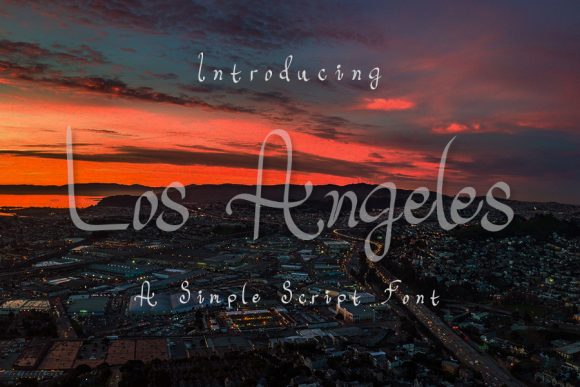
Creativefabrica Los Angeles Font
[Creativefabrica] Los Angeles Font
Лос-Анджелес - это стильный и невероятно элегантный шрифт сценария.
Он выглядит потрясающе на свадебных приглашениях, благодарственных открытках, цитатах, поздравительных открытках, логотипах, визитках и любом другом дизайне, который нуждается в рукописном прикосновении.